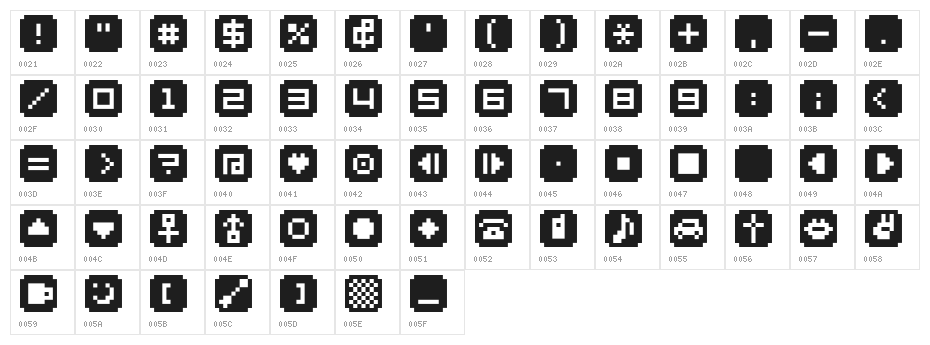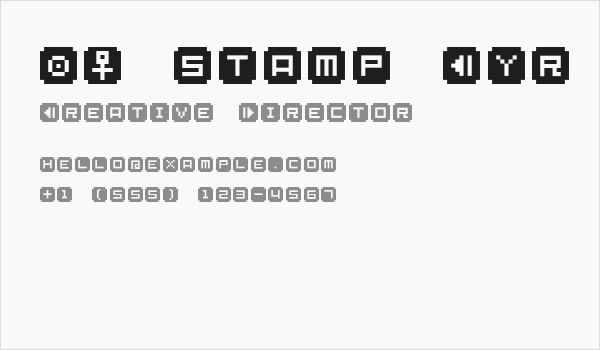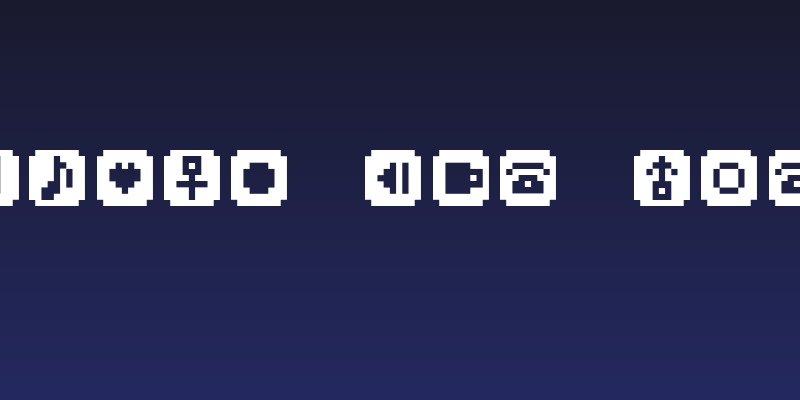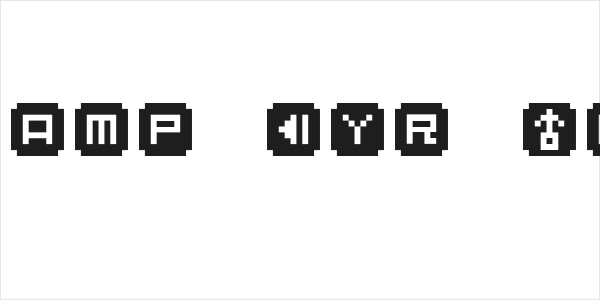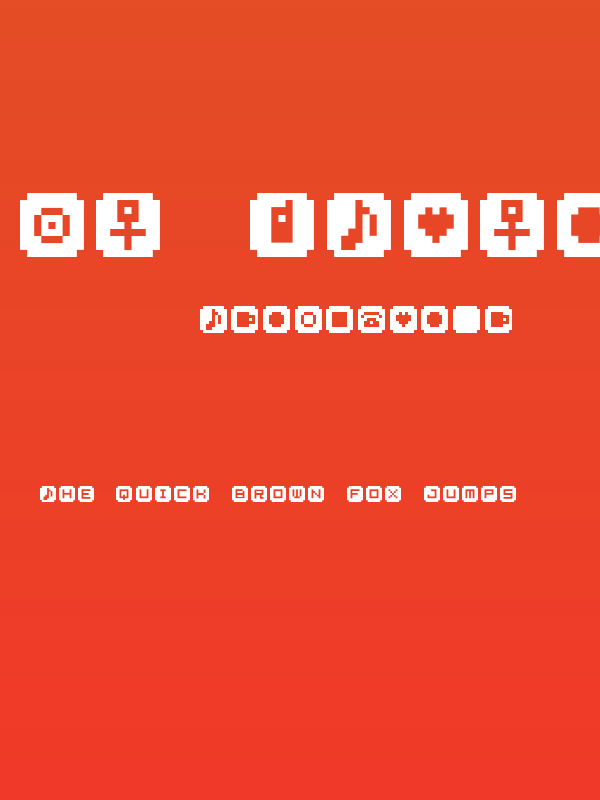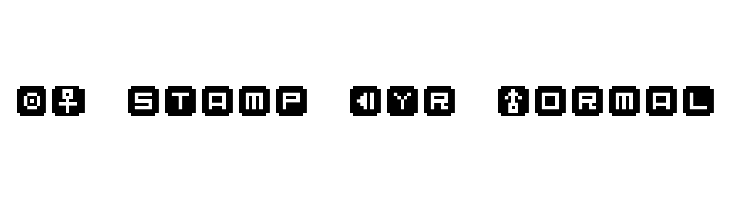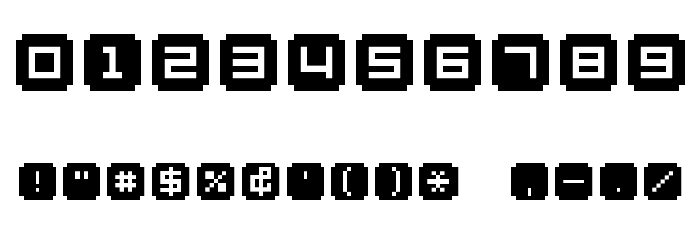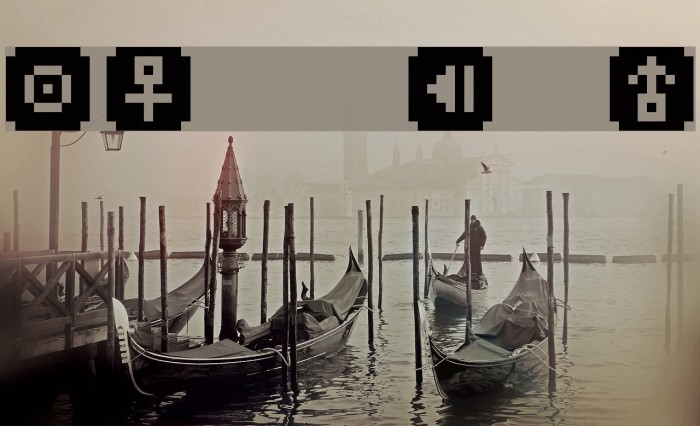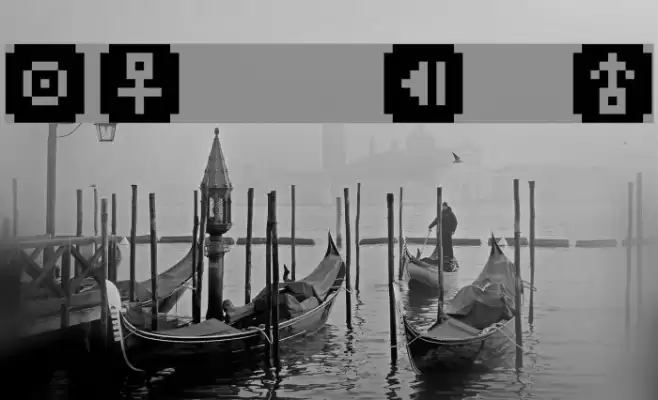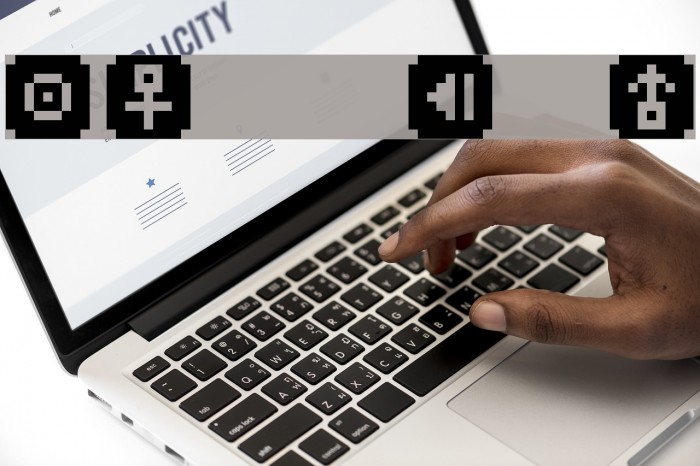
BM stamp Cyr Normal Font
| Gesamtstil | Vintage |
| Anwendungsfall | Logos, Headlines, Digital Art |
| Vorgeschlagene Projekte | Ideal for retro-themed video games, digital art projects, or any design work that seeks to capture the essence of early digital displays. |